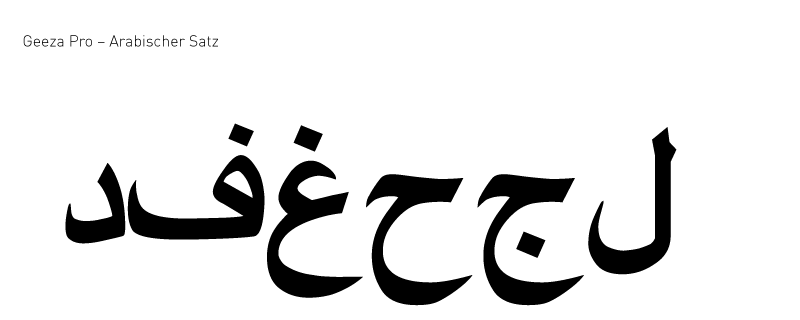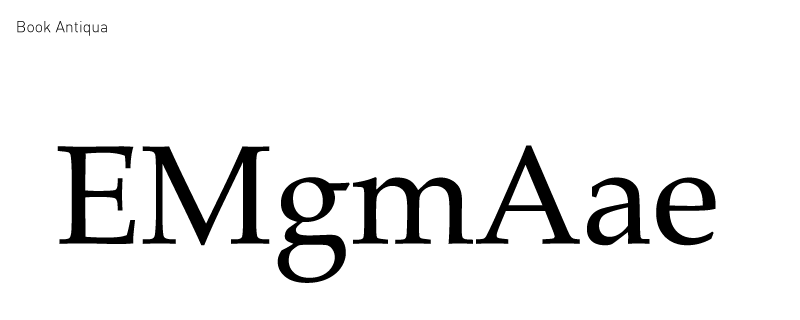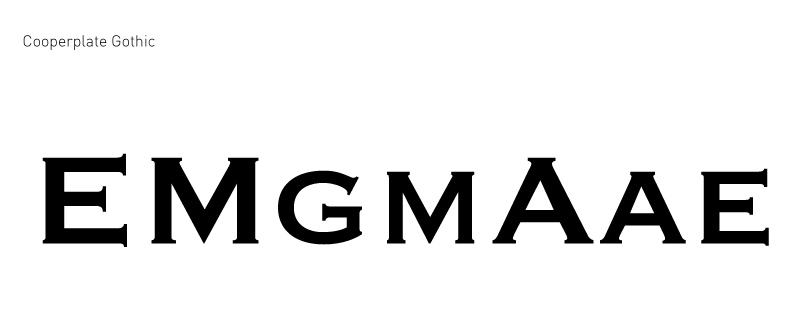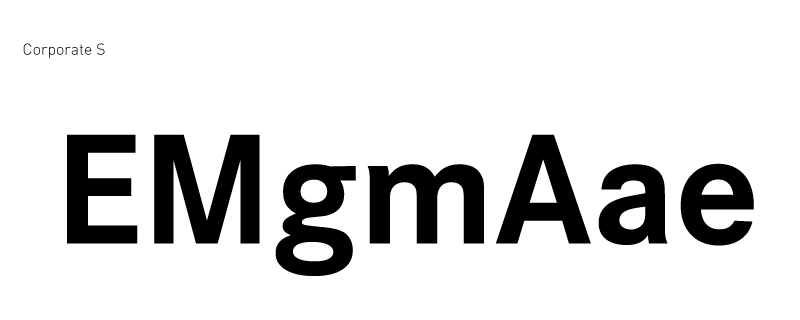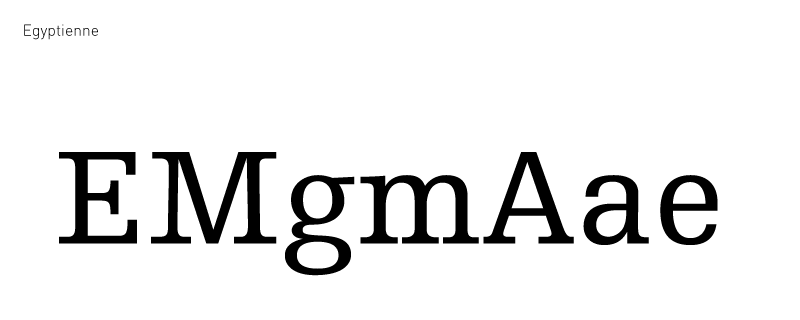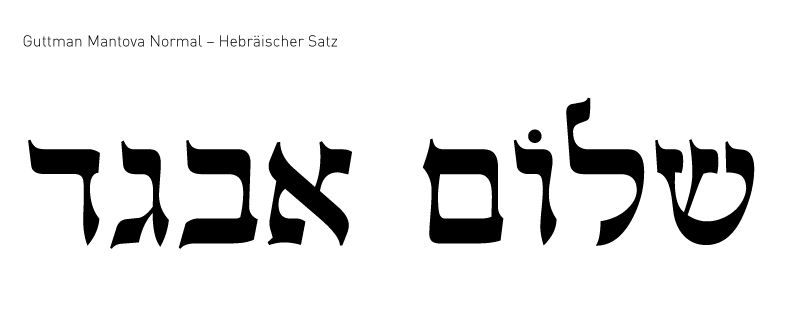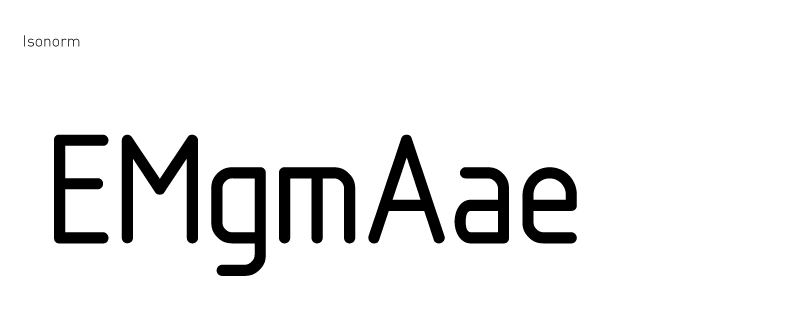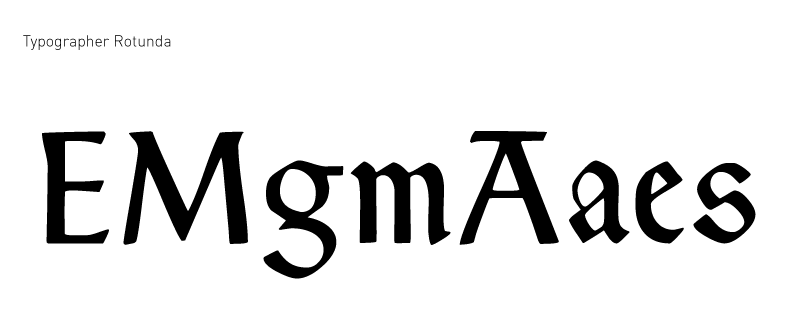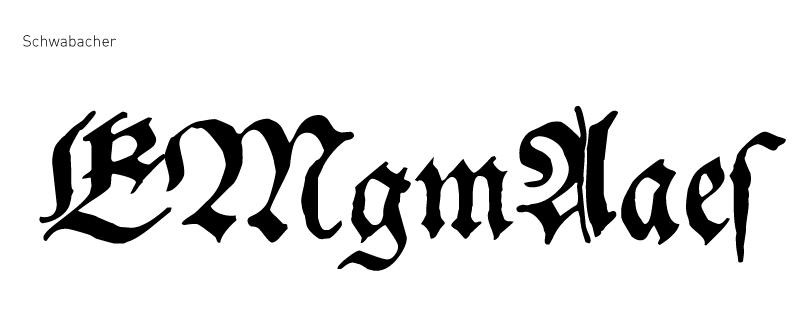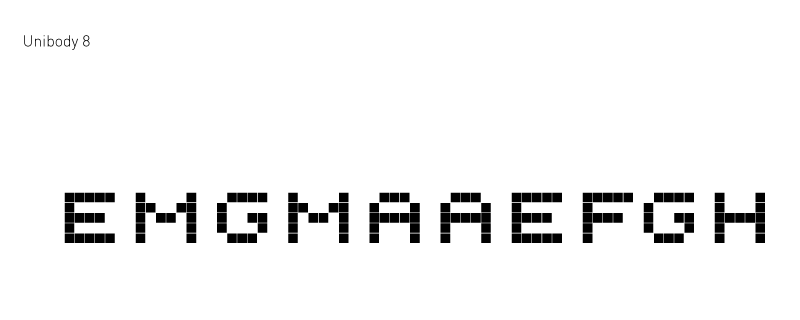
Die Matrix Beinert wurde nicht nur für den
philologischen Gebrauch entwickelt, sondern insbesondere
für den digitalen, typographischen Workflow in
Medienhäusern, Designstudios und Werbeagenturen.
Deshalb berücksichtigt sie bereits auf der ersten
Hierarchieebene (Hauptgruppen) für die
Unternehmenskommunikation wichtige Corporate Typography
Fonts (Schriftsysteme, CD-Schriften, DIN- ISO- und
OCR-Schriften) und Fonts für elektronische
Benutzeroberflächen und Lichtprojektionen (z.B.
Bildschirme, Internet, Beamer, Laser etc.).
Um
der babylonischen Schriftenvielfalt, modernen
Auftragsstrukturen und dem Ausbildungsniveau im Segment
der digitalen Typographie gerecht zu werden, wurden
sowohl Hauptgruppen für Druckschriften im Sinne der
klassischen Buch- und Lesetypographie als auch
Hauptgruppen für die moderne Unternehmens- und
Medienkommunikation geschaffen. Durch diese
Neugruppierung ist es nun auch für einen User mit
geringen typographischen Kenntnissen möglich,
Druck- und Screen-Schriften zumindest auf der obersten
Hierarchieebene plattformunabhängig auf jedem
Personal Computer sinnvoll zu ordnen, was mit anderen
Klassifikationsmodellen (Vox, Thibaudeau, Novarese,
Alessandrini-Codex, British Standard, etc.) nicht möglich
ist. (Quelle: Matrix
Beinert).
Die in den Jahren 2001-2005 entstandene
Klassifikation ist bemüht, sowohl das entstandene
Wissen um den Bleisatz, als auch jenes des digitalen
Satzes zu berücksichtigen.
Das herrschende
Durcheinander
- (Mac/PC/Linux/UNIX [Plattform, Betriebssystem],
- PS1/ TTF/OTF/XSF [Schriftdateiformat],
- Adobe/Linotype/Monotype/Bitstream/URW++/Elsner und Flake [Foundry],
- West-/Osteuropa/Türkisch/Griechisch/Latin I/Latin II/Unicode [Zeichensatz] usw.)
wäre durch das von Beinert vorgeschlagene
Klassifikationsbeispiel beseitigt:
Schriftgattung:
Antiqua
Hauptgruppe:
Antiqua
Untergruppe [Schriftart]:
Klassizistische
Antiqua
Nebengruppe:
Bodoni-Varianten
Schriftbezeichnung:
Bauer Bodoni ®
Schriftstil:
Kursiv
Figurenverzeichnis:
Mitteleuropa (nach ISO),
Mac
Bibliothek: Linotype ®
Library 1996
Technik: PostScript
1
Schriftgestalter: Giambattista
Bodoni (1790)
Quelle: Fundicion
Tipografica Neufville, S.A. 1926
Überarbeitet:
Jost, Heinrich 1926/1927 und Höll,
Lois
Distributor: Linotype-Hell AG
®, Adobe Systems Incorporated ® (w.
o.)
Mit dieser Beschreibung dürften keine
Fragen mehr zur vorhandenen (digitalen) Schrift offen
bleiben.
Schriftklassifikation Matrix Beinert für das